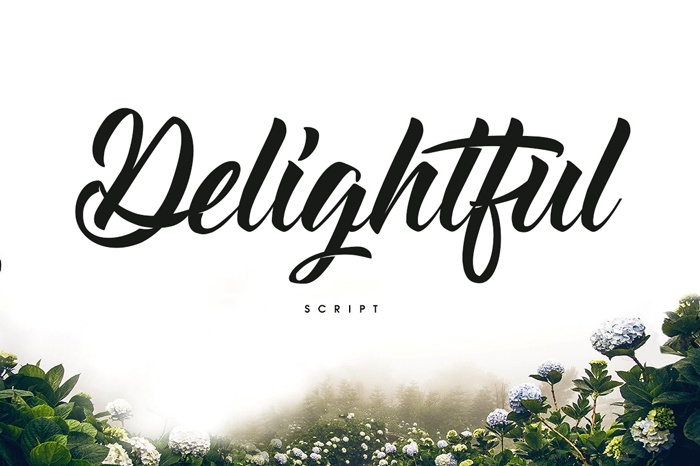
Delightful Script Font – Fonte Grátis
Delightful Script Font
A fonte ‘Delightful Script Font’ oferece uma experiência visual única para textos e design gráfico. Com sua caligrafia elaborada e detalhada, a fonte é ideal para criar mensagens emocionantes e memoráveis. Ela também permite a criação de logotipos incríveis, cartazes impactantes e até mesmo layouts de blog que destacam suas ideias com estilo. A Octotype tem cuidado em cada traço da fonte para garantir que ela seja perfeita tanto para uso profissional quanto para projetos pessoais. Se você está procurando uma fonte que traga vida ao seu design, ‘Delightful Script Font’ é definitivamente um item de primeira escolha a considerar. Sua disponibilidade em licença comercial também lhe dá liberdade para usá-la onde quiser.
Designer: Octotype